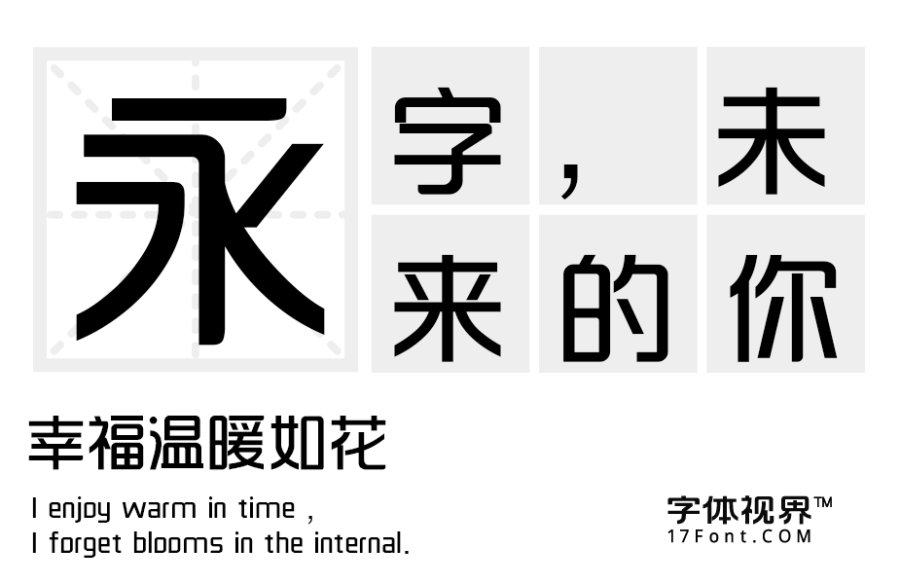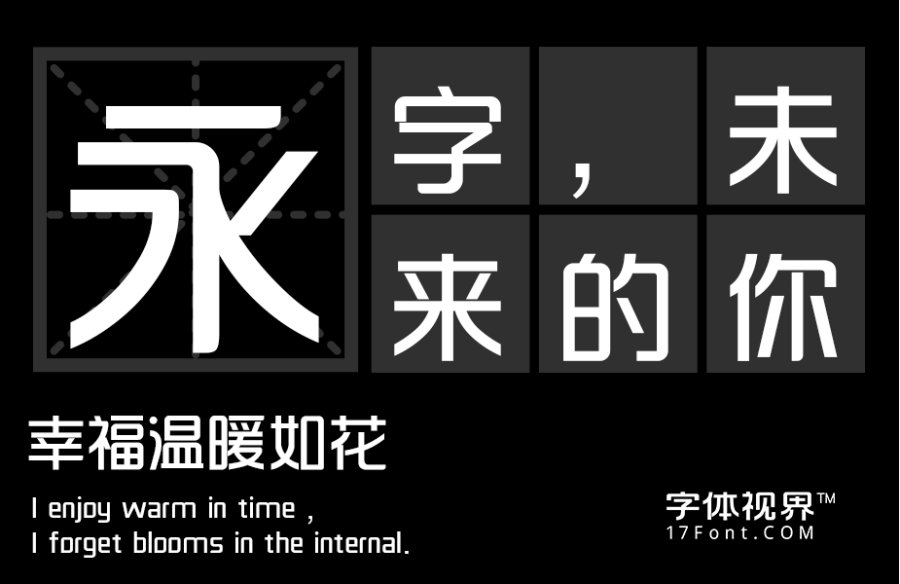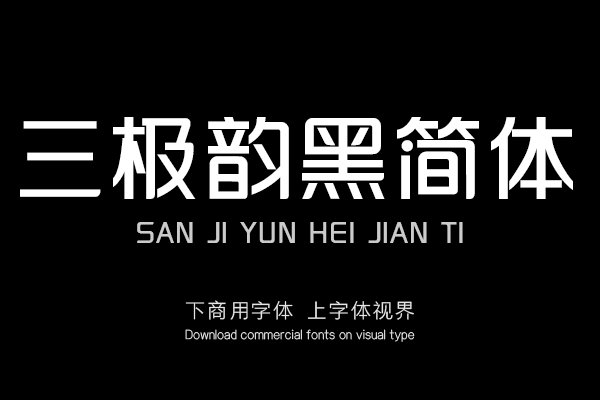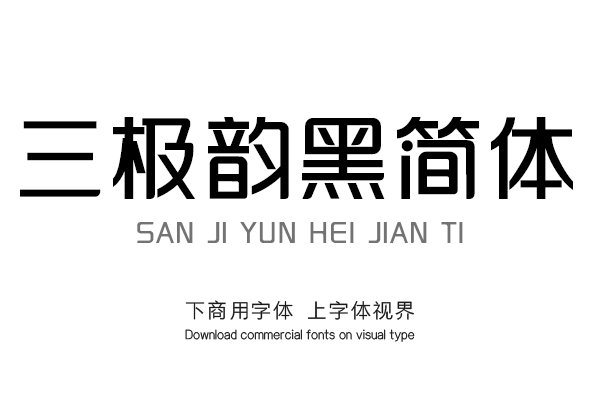
这款字体的笔画轮廓由直线和转角弧线构成,横竖笔画交叉处、折笔处和部分的收笔处呈四分之一圆弧形状,撇、捺笔画镜像均匀对称,字形充满整个字面框,重心稳定。风格刚中带......购买须知:“下载服务费”与“字体VIP”所获得字体 仅用于个人非商用, 商用请联系付费授权。本字体为电脑用字,手机没有root权限不支持直接手机换字(手机如何root,请自行百度搜索教程)。购买前请先 了解清楚后再付款 ,字体为虚拟产品无法回收 一旦购买不支持退款。